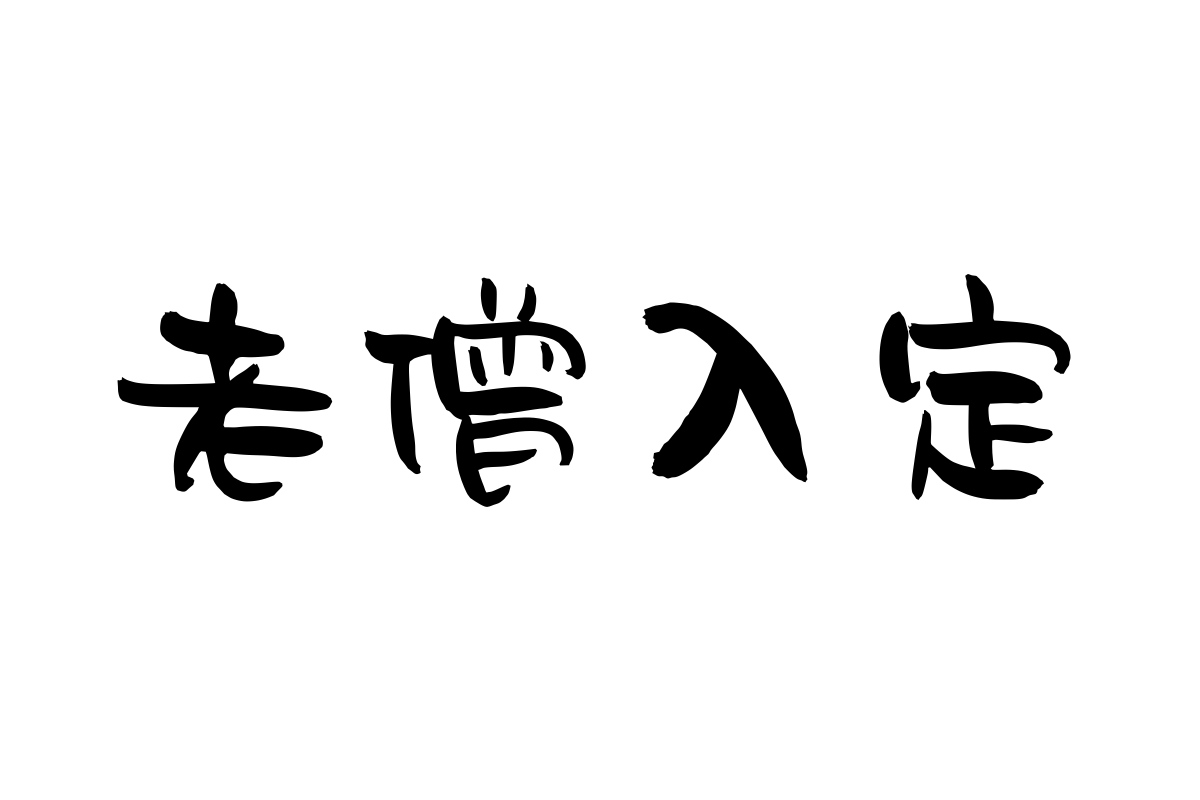
汉仪尚巍自由体是一款具有独特风格的免费中文字体。它由汉仪公司设计开发,旨在为用户提供一种新颖、独特的视觉体验。这款字体采用了现代的设计理念,融合了传统与现代的元素,使得文字更加生动有趣。
汉仪尚巍自由体的特点如下:
1. 字形优美:该字体的字形结构独特,线条流畅,给人一种优雅而富有艺术感的感觉。无论是书写还是印刷,都能呈现出优美的视觉效果。
2. 风格鲜明:汉仪尚巍自由体具有鲜明的个性和风格,适合用于需要突出个性和创意的设计项目。无论是广告、海报、书籍还是网页,都能展现出与众不同的效果。
4. 可定制性强:汉仪尚巍自由体提供了丰富的字重和笔画粗细设置,用户可以根据自己的喜好和需求进行个性化定制。此外,字体还支持自定义字符集,可以满足特殊需求的应用场景。
总之,汉仪尚巍自由体是一款具有独特风格的免费中文字体,适用于各种设计项目。它不仅能够提升设计的美感和创意性,还能满足用户对于个性化和定制化的需求。